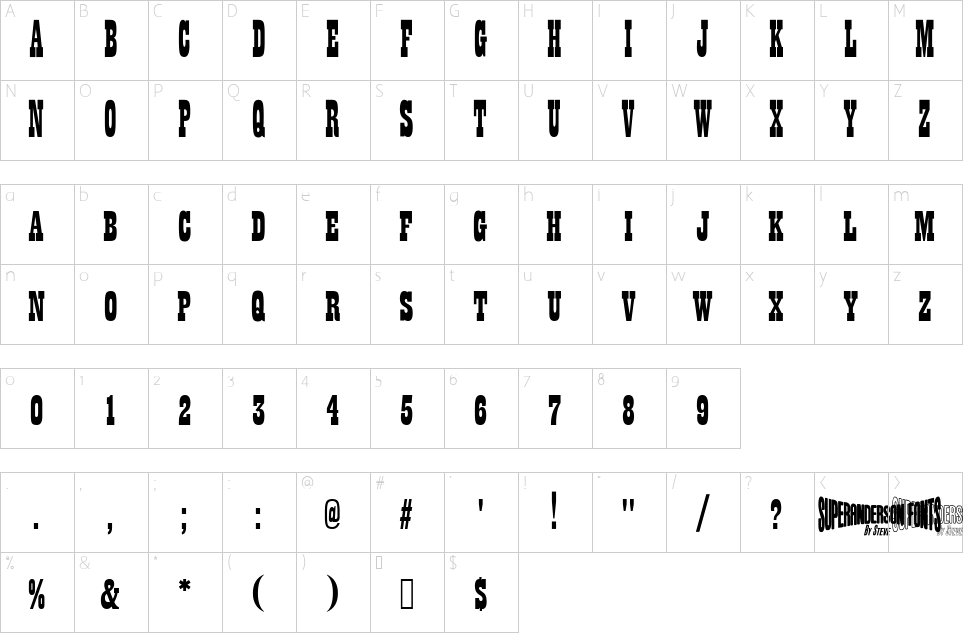
Anderson Thunderbirds Are Go Font – Download Grátis
A fonte “Anderson Thunderbirds Are Go” surge como uma escolha incrível para designers e criativos buscando uma maneira vibrante e assertiva de destacar seu trabalho. Ela foi criada por Steve Ferrera e já foi baixada mais de 40.000 vezes. Essa fonte não apenas traz um toque dinâmico e confiante à sua peça de design, mas também oferece uma versão compatível com sistemas operacionais Windows e Mac, garantindo que ela seja acessível para todos. Com sua alegria vibrante e disposição decidida, a “Anderson Thunderbirds Are Go” é uma ótima opção para quem deseja transmitir um forte e positivo impacto visual em suas criações.